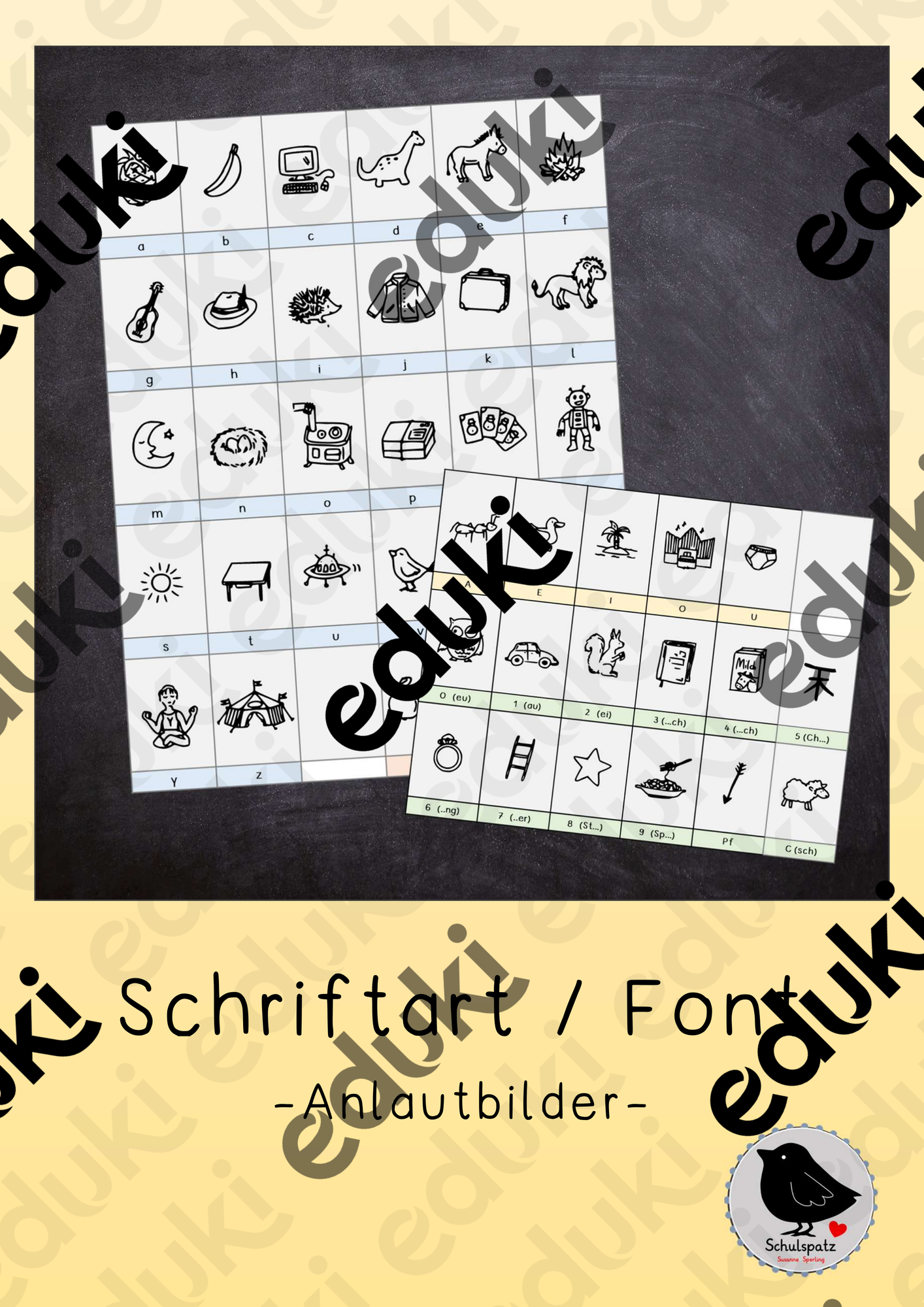
Mit dieser besonderen Schriftart kannst du ganz einfach über deine Tastatur Anlautbilder "schreiben" und so ansprechende Arbeitsmaterialien, Spiele, Plakate, Karteikarten erstellen und gestalten.
Erstelle z.B. Karteikarten mit "Geheimschrift" und biete sie als Freiarbeitsmaterial zum Rätseln an: Die Kinder hören den Anlaut, notieren diesen unter dem Bild und erhalten so ein Lösungswort.
Neben allen Buchstaben, stehen dir auch Umlaute, Doppellaute und besondere Buchstabenverbindungen zur Verfügung. Der Zeichensatz zeigt dir, welche Tasten mit welchem Anlautbild belegt sind.